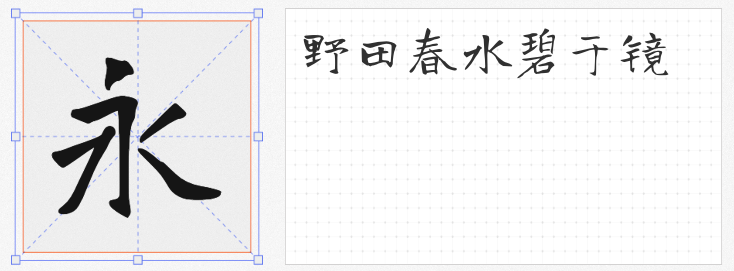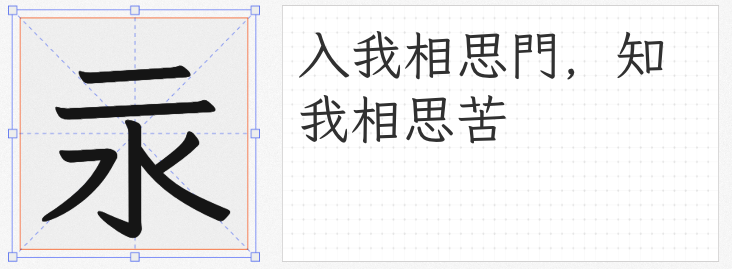
在平面设计中,书法字体以其独特的文化韵味与艺术表现力,成为提升作品格调的关键元素。本文精选四款免费可商用的书法字体,涵盖传统楷书、创新设计及城市文化主题,为设计师提供兼具实用性与艺术性的选择。
基于开源字体“演示秋鸿楷”拓展的寒蝉书体·春秋 秋鸿,以“春”与“秋”为灵感内核,将自然时序融入字形设计。其笔画粗细对比鲜明,横竖转折处保留毛笔书写痕迹,既有楷书的端庄,又带行书的灵动。例如,“春”字横画舒展如新芽破土,“秋”字撇捺收放似落叶飘零,适合文化海报、书籍封面等场景。
月星楷繁半宽Regular以古籍《洪武正韵》为字形参考,结合现代OpenType技术,实现“一简多繁”动态匹配。其笔画起收笔处融入篆书圆润感,中宫紧凑而外拓舒展,如“龙”字结构繁复却层次分明。该字体支持GB2312字符集,繁体字设计尤为考究,例如“辭”字笔画间留白透气,适合传统品牌标识、古籍排版等场景。作为全平台免费商用字体,其授权协议明确,安全性高。
基于开源字体“有字库龙藏体”拓展的寒蝉龙藏楷书,通过新增字重与笔画修复,强化了楷书的雄浑气质。其横画粗壮如骨,竖画挺拔如筋,例如“武”字戈钩斜挑有力,适合运动品牌、科技产品等需要展现力量感的场景。该字体同样采用SIL Open Font License协议,支持自由修改与再分发,为设计师提供深度定制空间。
作为全国首款城市定制字体,昆明海鸥体将红嘴鸥的灵动姿态融入汉字结构。例如,“昆”字嵌入站立鸥形,“鸥”字呈现飞翔动态,而“滇池”“春城”等词则通过笔画变形展现海鸥觅食、滑翔等场景。该字体由书法家叶根友团队设计,6763个汉字覆盖日常使用需求,适合文旅宣传、文创产品等场景。
这四款字体或承古法之韵,或融科技之新,或载城市之魂,为设计注入文化深度与视觉张力。无论是追求传统美学的项目,还是需要创新表达的场景,它们都能成为设计师的得力工具。